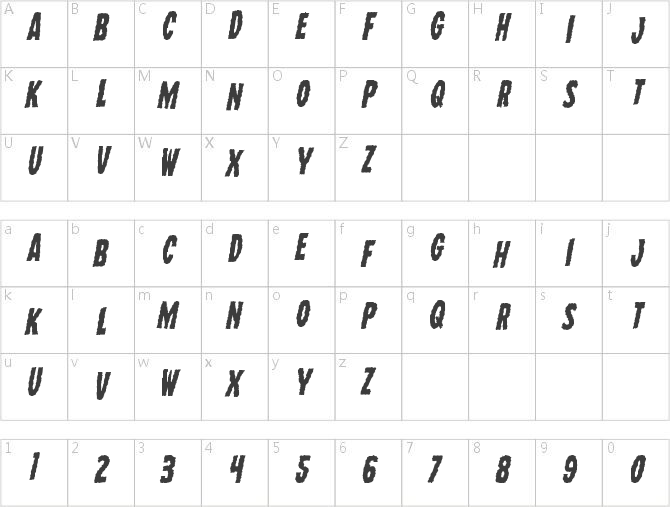
Wolf Brothers Staggered Italic
Wolf Brothers Staggered Italic介紹
Wolf Brothers Staggered Italic字體字庫是一款讓人賞心悅目、百看不厭的英文字體,適合各類廣告和產品包裝設計應用,字體大小0.15MB,格式為ttf字體,上傳用戶是昊天金誠,作者/版權方為未知